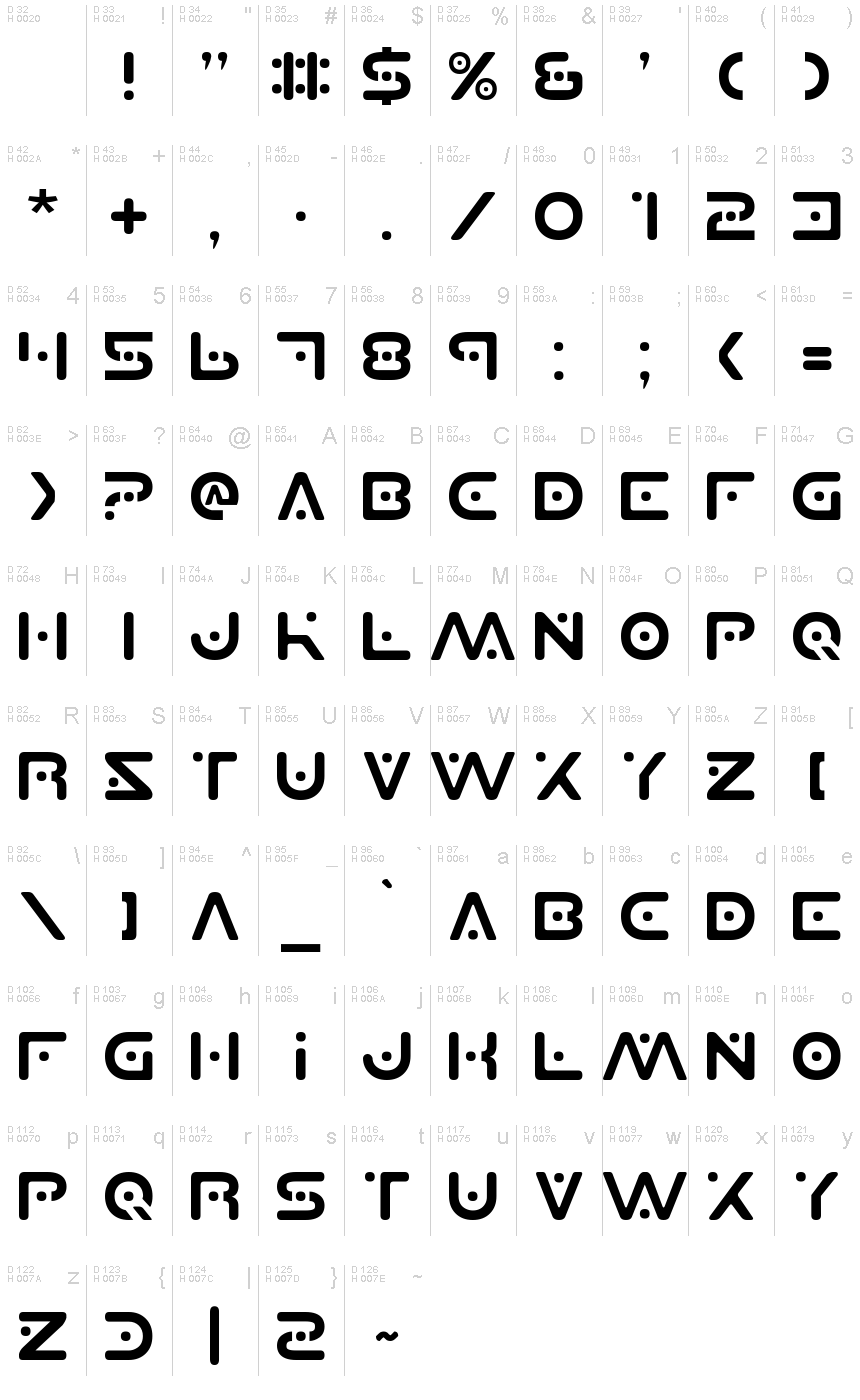
Planet S — это эффектный дисплейный шрифт от дизайнера Дэниела Задорожного. Его футуристичная эстетика с элегантными широкими начертаниями излучает современность и технологичность. Четкие угловатые формы и геометрическая точность придают шрифту уверенность и авторитетность, что делает его идеальным выбором для заголовков, брендинга и других дизайн-проектов, где важен сильный визуальный акцент.
Универсальность этого шрифта выходит далеко за рамки его яркого внешнего вида. Увеличенная ширина знаков обеспечивает отличную читаемость в крупных кеглях, что отлично подходит для создания выразительных вывесок, плакатов и интерфейсов. Дизайнеры, стремящиеся создать прогрессивный и инновационный образ, найдут в Planet S ценный актив для своего творческого инструментария.
Planet S
Daniel Zadorozny